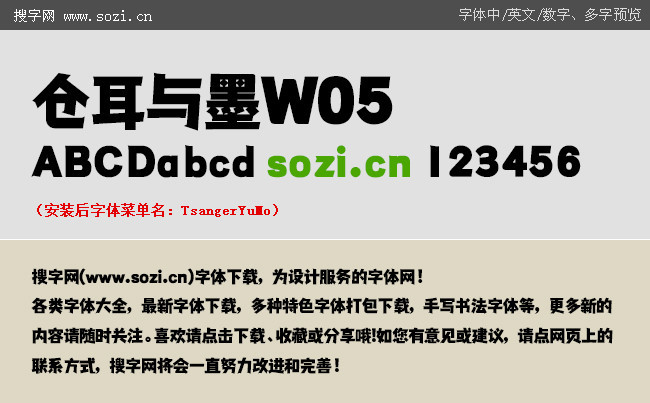
倉(cāng)耳與墨W05
搜字網(wǎng)提供一款倉(cāng)耳與墨W05中文藝術(shù)字體下載,倉(cāng)耳與墨字體是由倉(cāng)耳字庫(kù)推出的一款免費(fèi)字體,共收容漢字6763個(gè),英文及標(biāo)點(diǎn)等常用字符245個(gè)。該字體包含5個(gè)字重,風(fēng)格偏向現(xiàn)代創(chuàng)意字體,強(qiáng)調(diào)厚重與力量,具有醒目、有力和前衛(wèi)的特點(diǎn)。